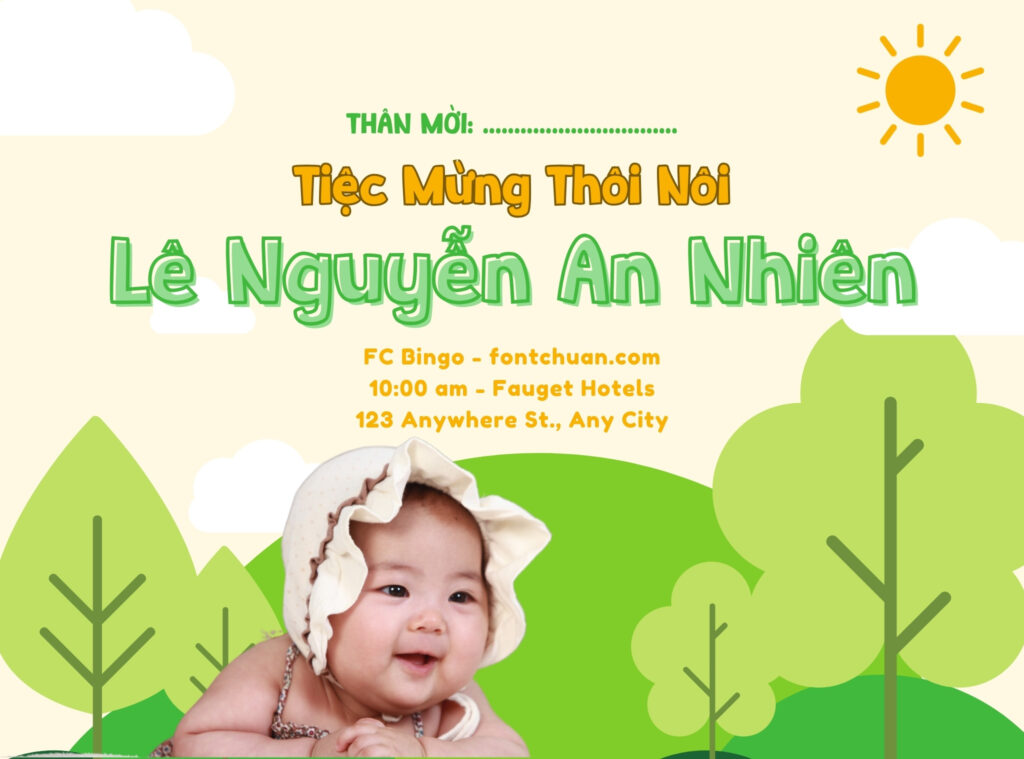
Font FC Bingo Việt Hóa
BINGO là một font chữ hiển thị mang phong cách hoạt hình, được thiết kế bởi Pinisiart và phát hành vào khoảng năm 2023. Với các đường nét đậm và hình dạng vui nhộn, BINGO mang lại cảm giác tươi vui và năng động, đồng thời có thể được sử dụng như một Font Lễ hội để tạo điểm nhấn sinh động cho các ấn phẩm sự kiện, poster, banner hoặc các dự án thiết kế dành cho trẻ em. Font này phù hợp cho các dự án thiết kế như tiêu đề, poster, bao bì sản phẩm, truyện tranh, sách, đồ chơi và các ấn phẩm sáng tạo khác.
Font FC Bingo Việt Hóa được việt hóa để hỗ trợ tốt cho tiếng Việt bởi Font Chuẩn và chia sẻ toàn bộ miễn phí. Mặc định font hỗ trợ tiếng Anh và nhiều ngôn ngữ Latin khác, mở rộng khả năng ứng dụng cho nhiều dự án quốc tế, đáp ứng nhu cầu đa dạng của bạn đọc và hỗ trợ ứng dụng thực tế trong các dự án thiết kế.
Với cấu trúc chữ đậm nét, thiết kế ngộ nghĩnh và phong cách độc đáo, FC BINGO phù hợp cho các thiết kế yêu cầu sự nổi bật và sáng tạo. Đặc biệt, font này thích hợp cho các ngành nghề như quảng cáo, thiết kế bao bì và lĩnh vực giáo dục, nơi cần sự kết hợp giữa thẩm mỹ vui tươi và chức năng truyền tải thông điệp.